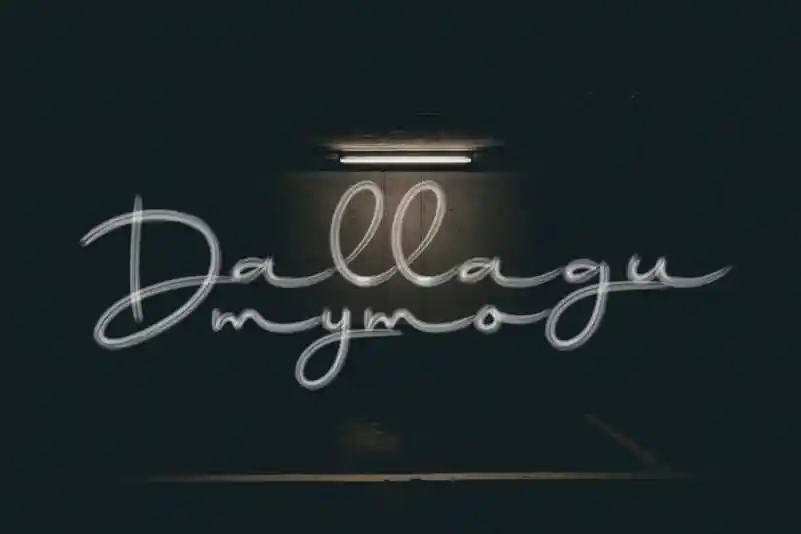
Dallagu Brush Font – Download Grátis
Dallagu Brush Font é uma excelente opção para quem busca um estilo elegante e distintivo, ideal para qualquer projeto que deseje destacar sua originalidade. Desenvolvida pelo designer andikastudio, essa fonte brush se destaca pela sua característica de escrita a mão fluida, cheia de vida e personalidade. Suas formas redondas e suaves capturam o encanto do desenho à mão, proporcionando um toque autêntico que não poderia ser encontrado em outras fontes. Perfeito para gráficos pessoais ou corporativos, Dallagu Brush Font é perfeita para projetos web, impressão ou qualquer outro tipo de design onde uma forte identidade visual seja importante. Com sua elegância e tempo de vida imbatível, essa fonte é o ideal para quem procura um toque único que brilhe em cada projeto. Experimente Dallagu Brush Font e transforme seus projetos em algo extraordinário.